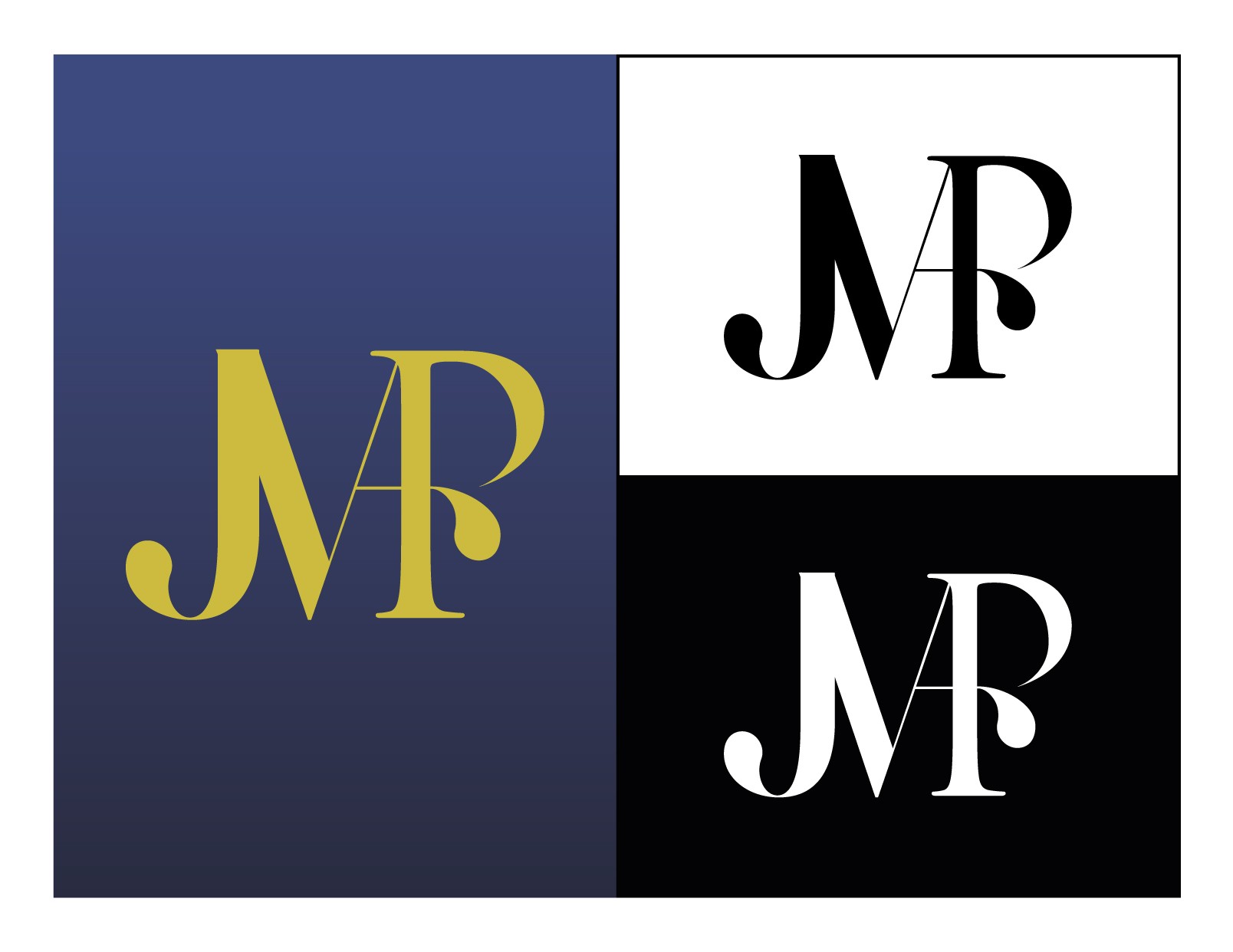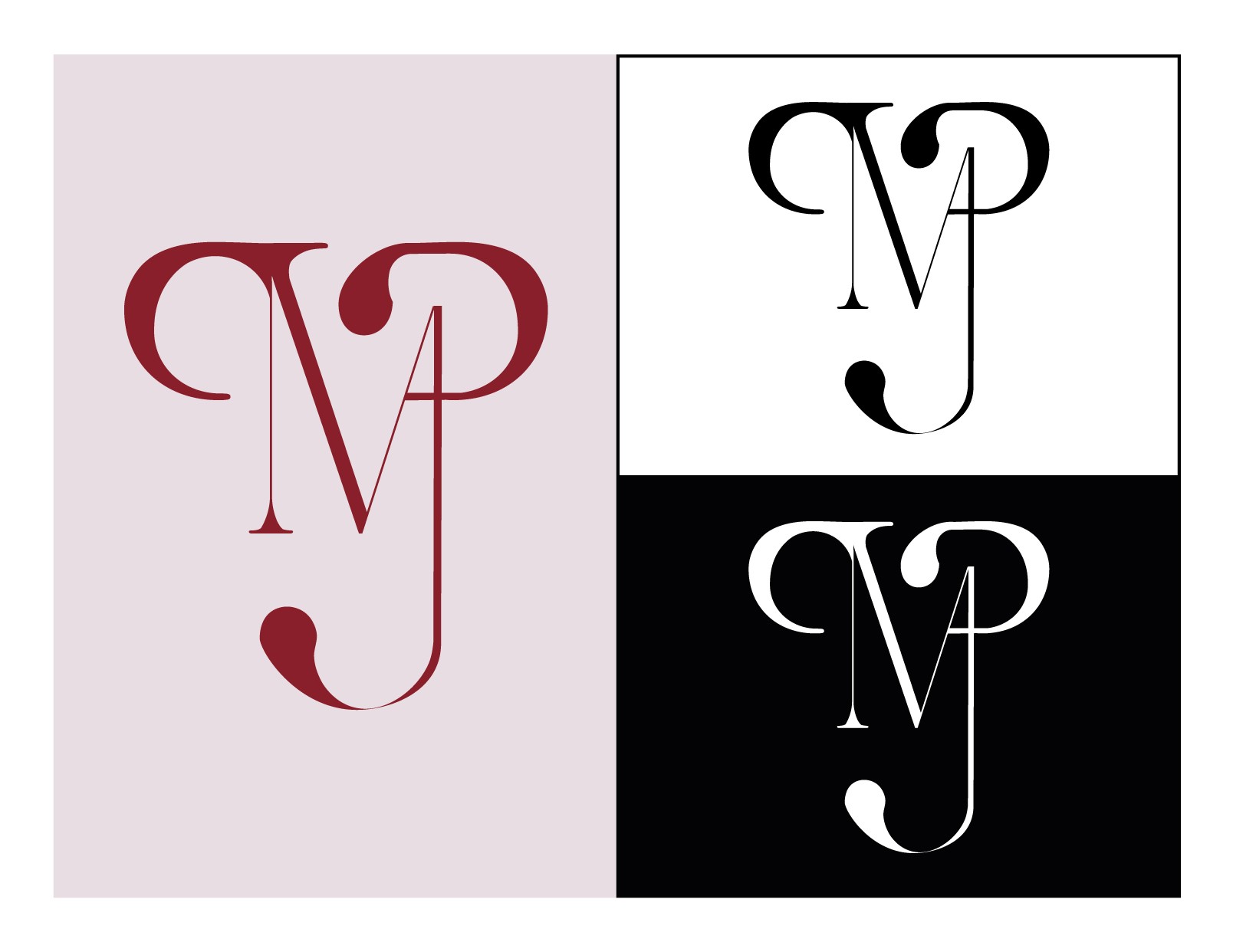
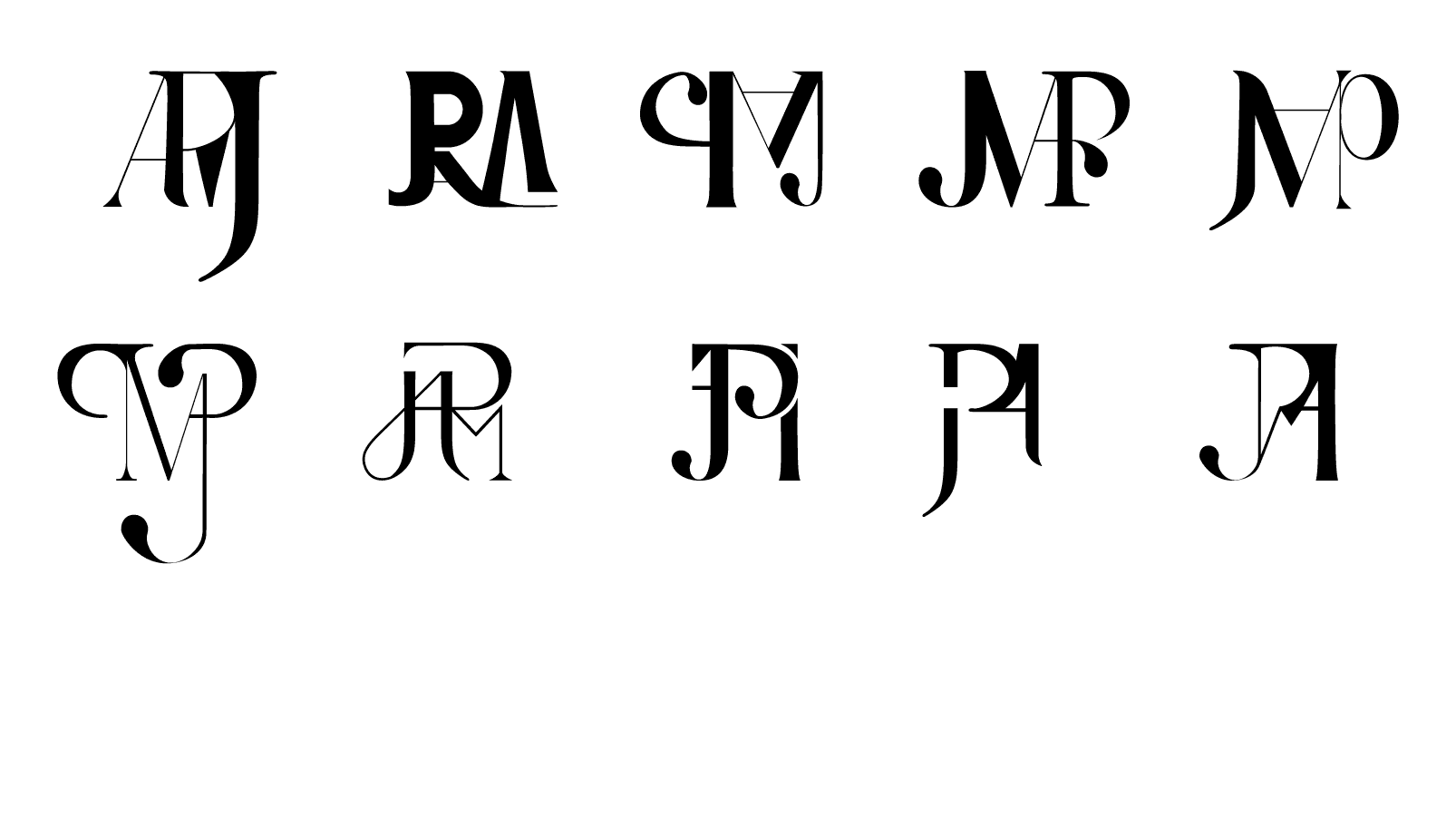
Creación de monogramas a partir de las iniciales de mi nombre, construyendo un logo en óptimas condiciones, con fusiones tipográficas, y añadiendo un estilo propio.